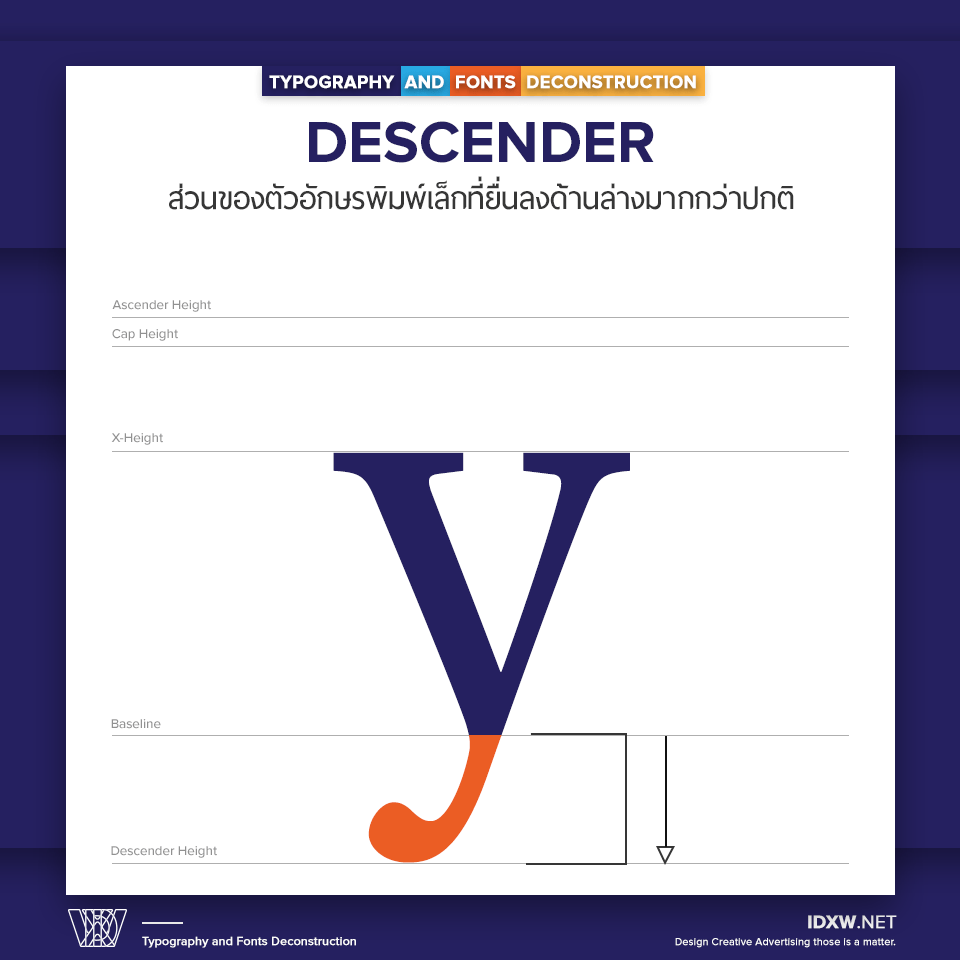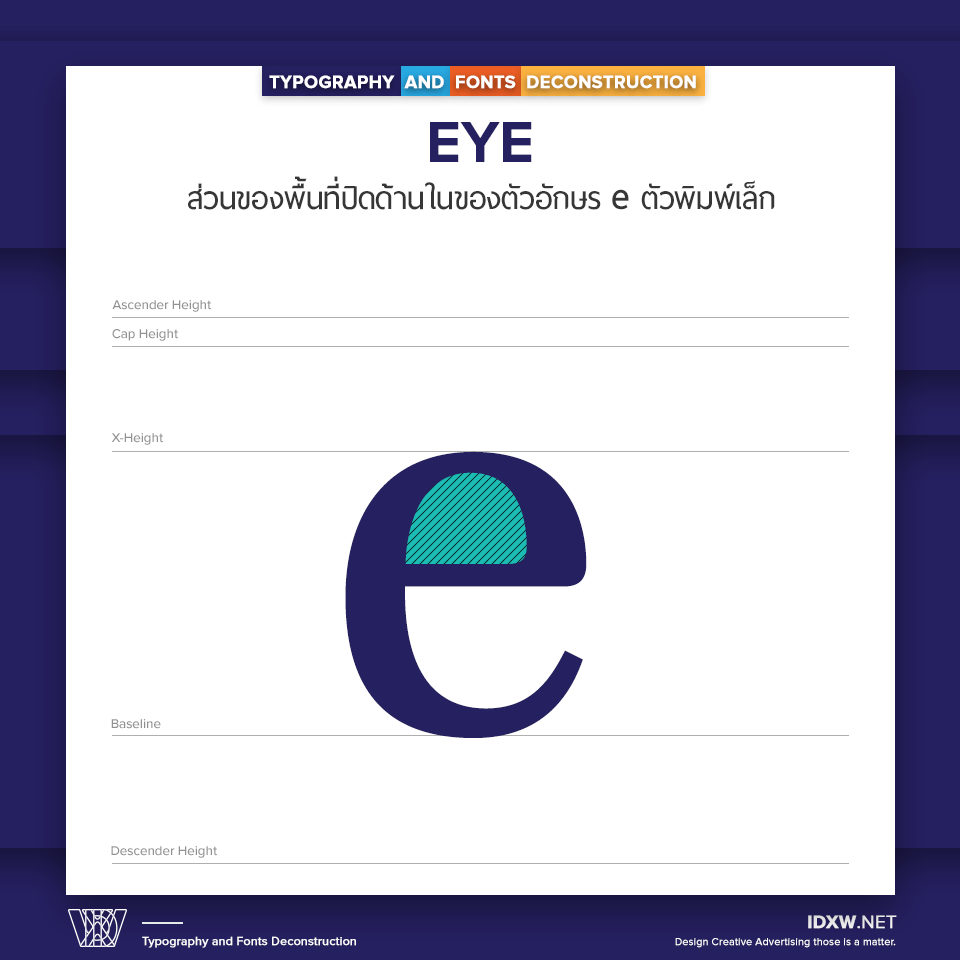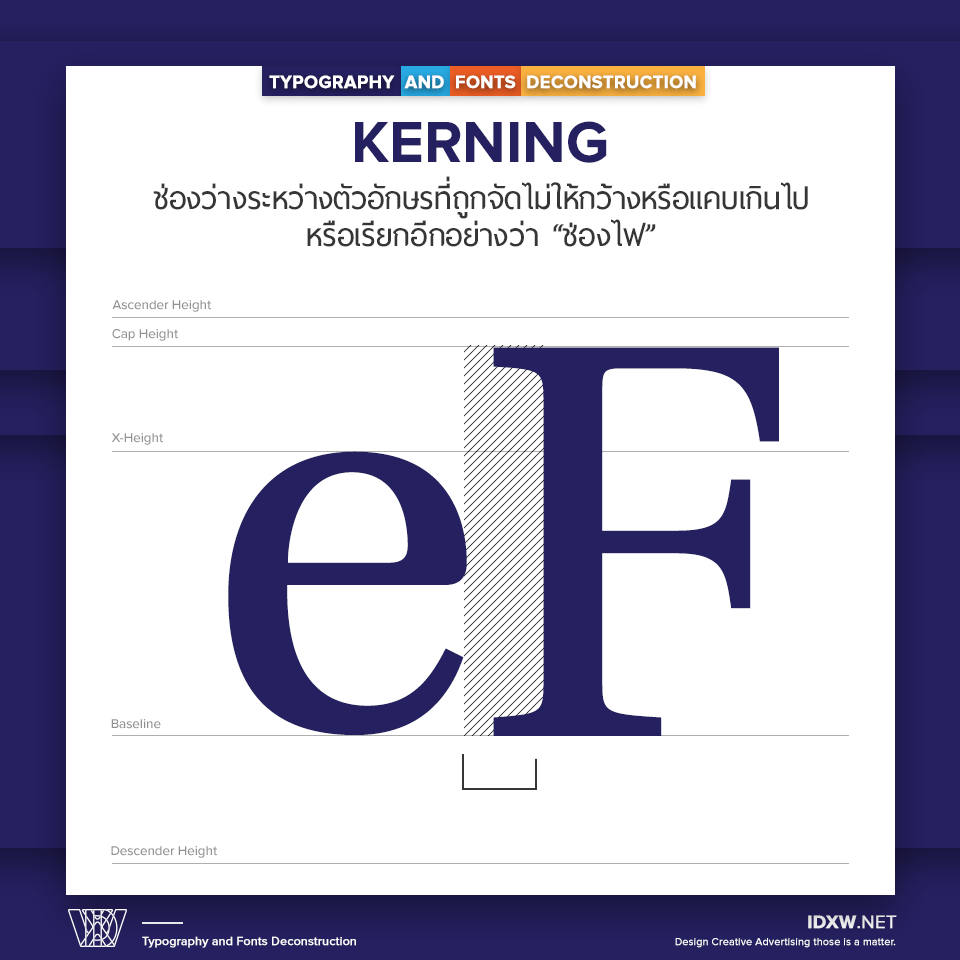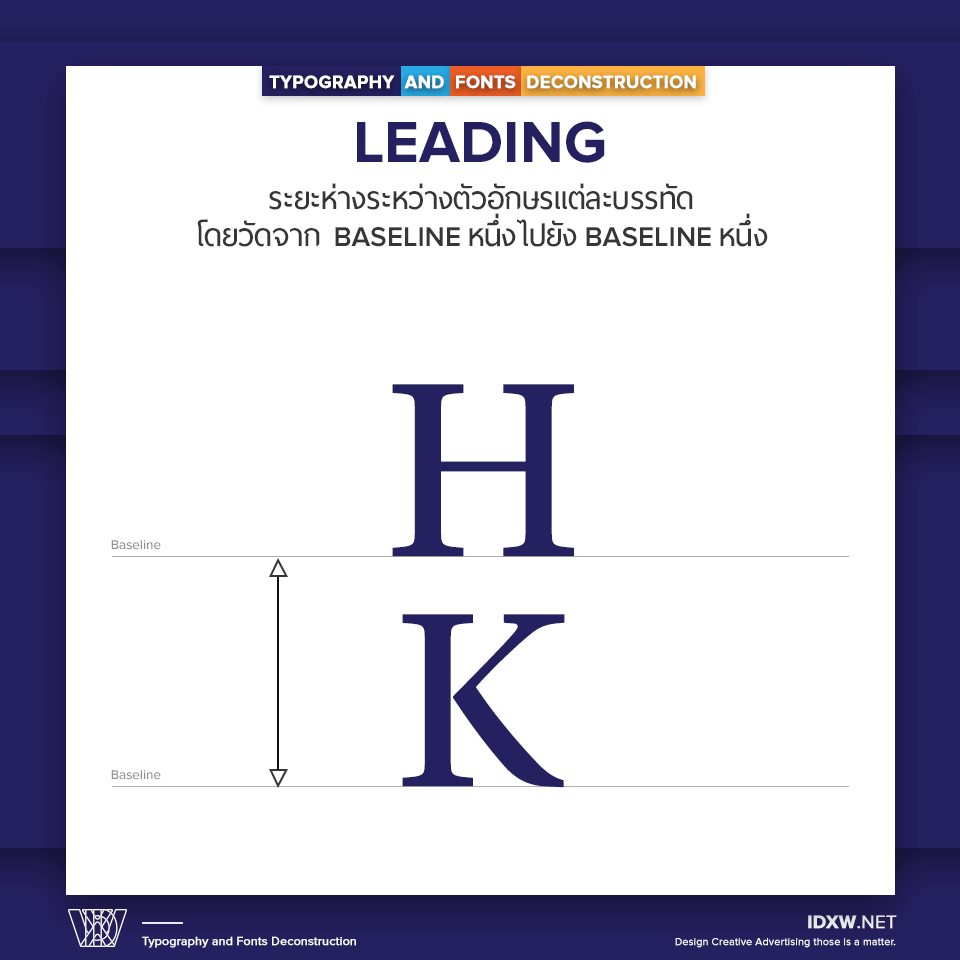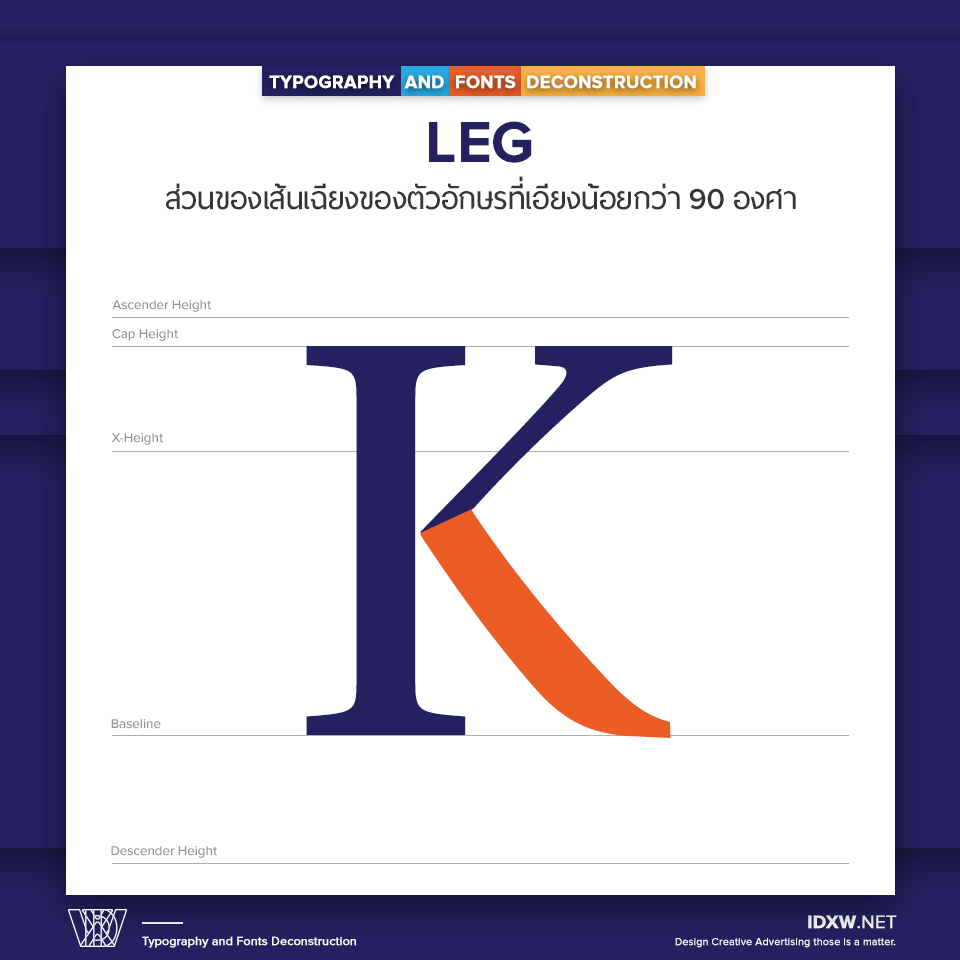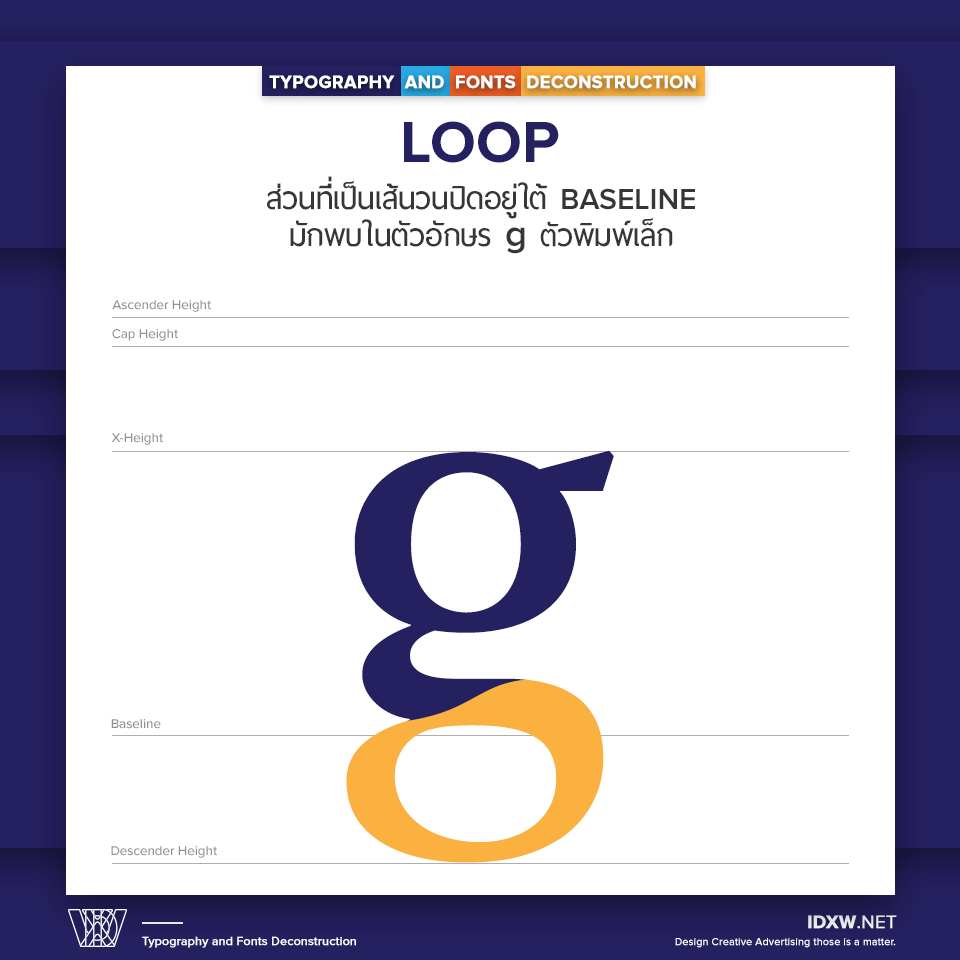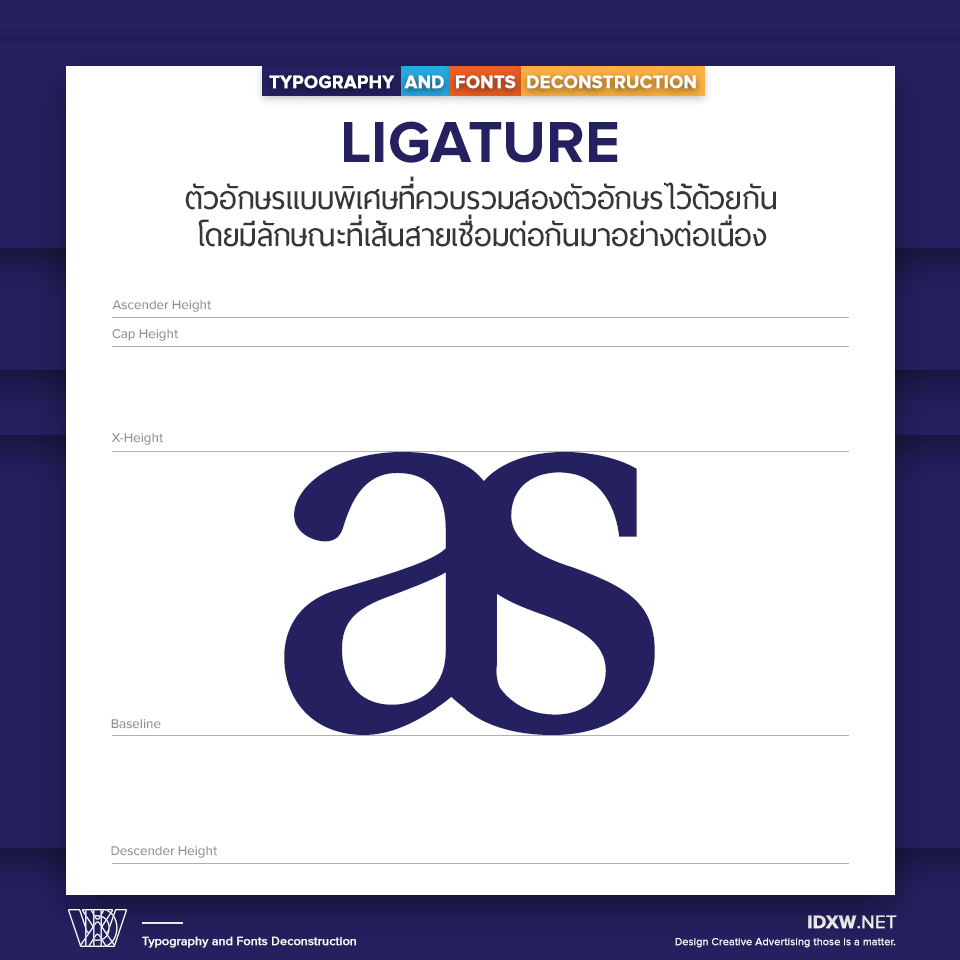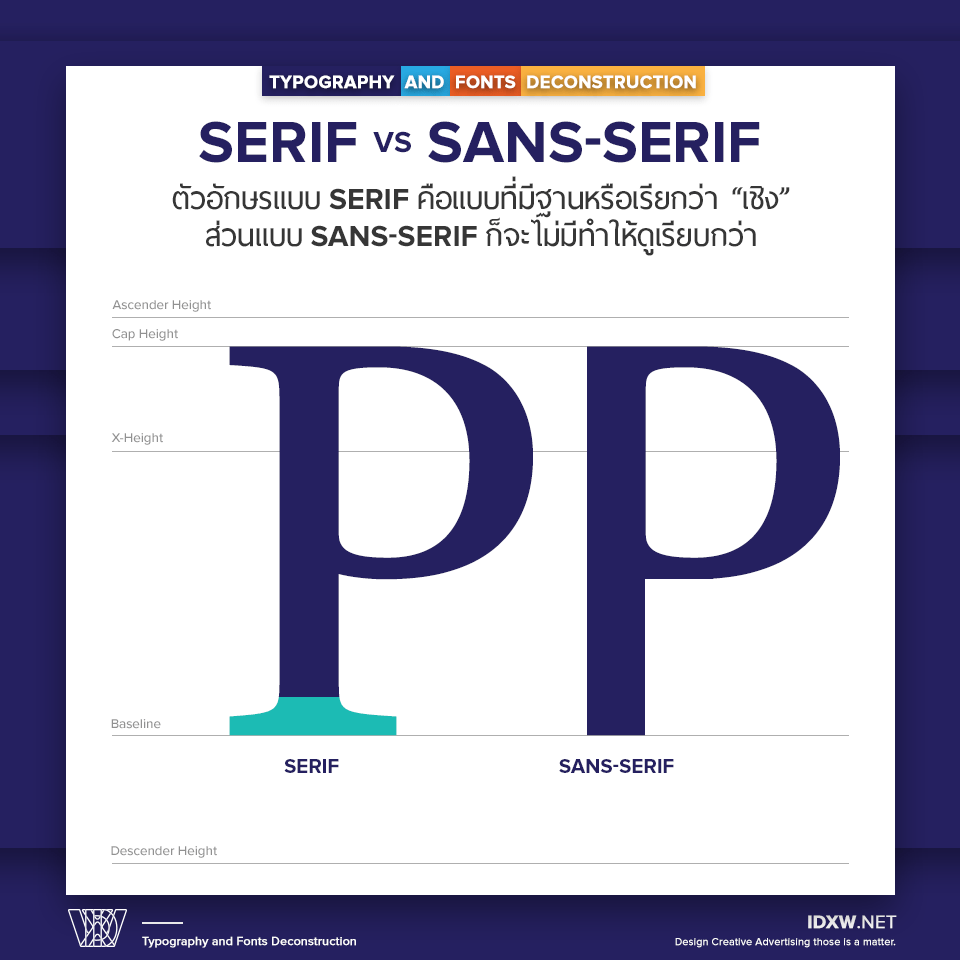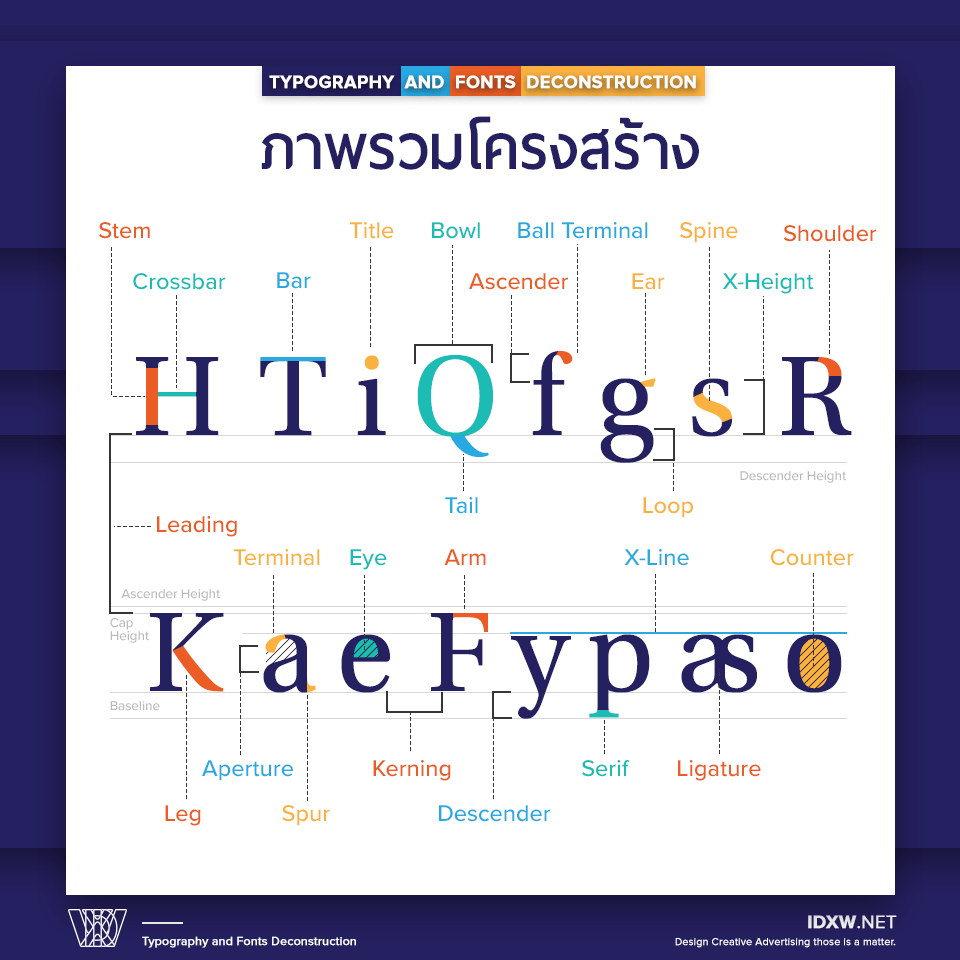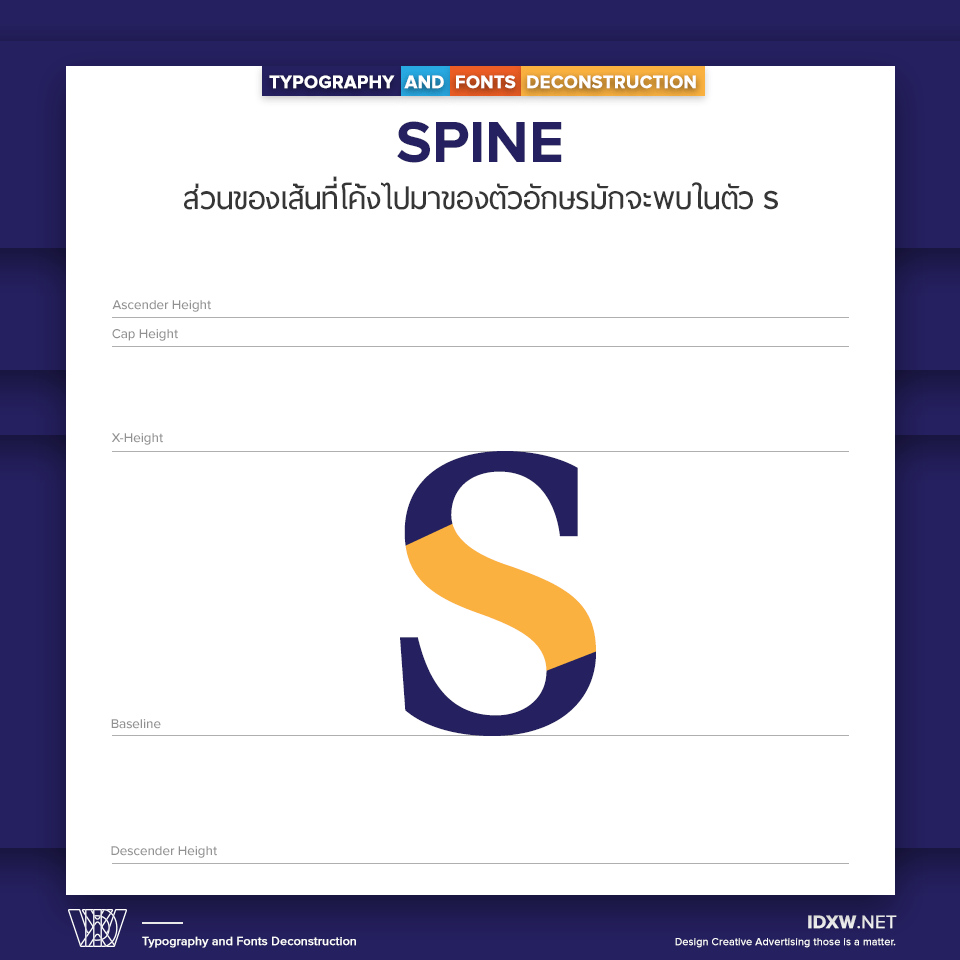
วันนี้เรามาลองศึกษาโครงสร้างของ Typography และ Fonts กันว่าอะไรเป็นอะไรบ้าง ให้ได้รู้จักองค์ประกอบของโครงสร้างๆต่างที่รวมกันเป็น Fonts เก็บไว้ใช้อ้างอิงหรือศึกษาเพิ่มเติมได้อีก ซึ่งที่จริงแล้วศาสตร์แห่ง Typography มีความซับซ้อนและลึกซึ้งกว่านี้อีกเยอะเลย เพราะยังมีเรื่องของการสร้างฟ้อนต์ การจัดเรียงตัวพิมพ์ หรือ เรื่องของไทป์เฟซแบบต่างๆอีกมากมาย จะทยอยเอามาฝากกันในคราวต่อๆไปแล้วกันนะครับ